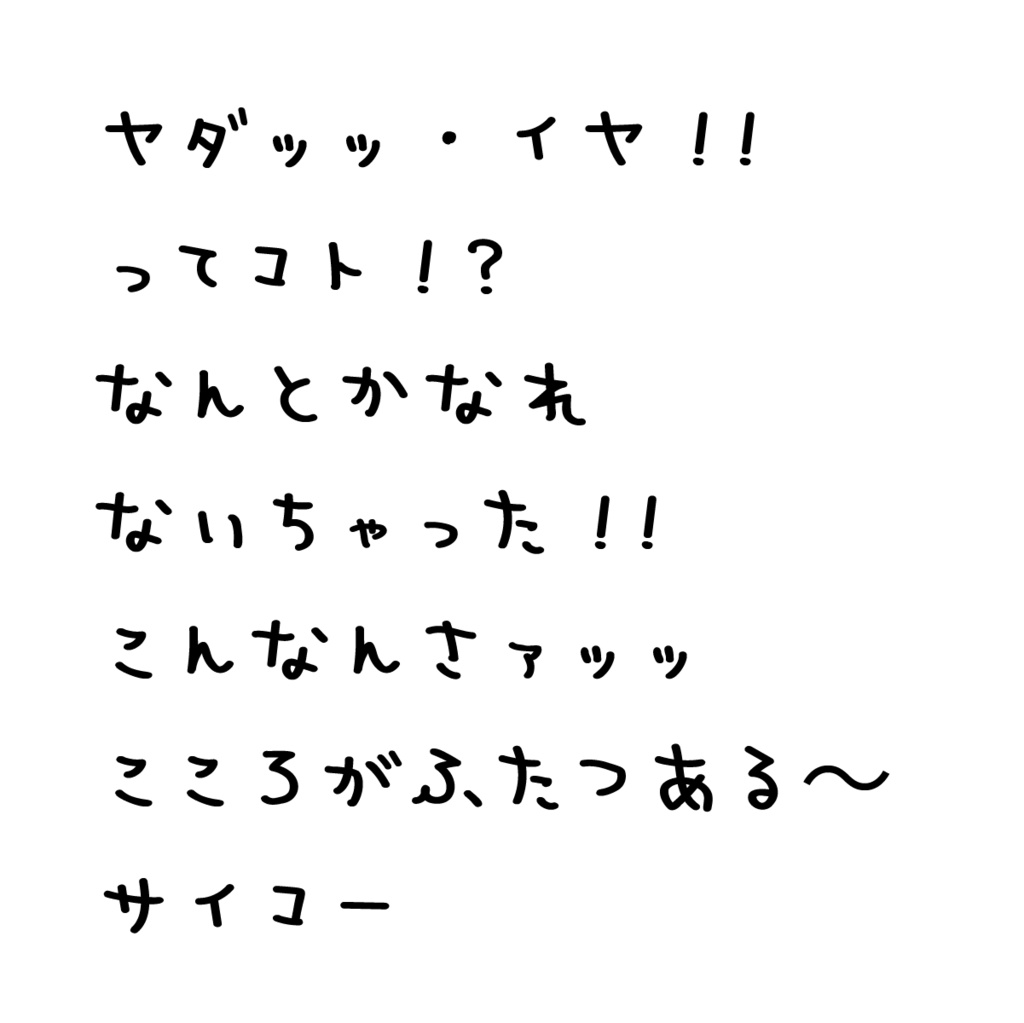
ちいかフォント(フリーフォント)
【25.04.02更新】 ・一部の文字を修正対応いたしました。 --- ちいかフォントは、「文字が、ちいかわのナガノ先生の字に似ているね。」と知人に言われたことをキッカケに制作した手書きフォントです。 自前の手書き文字を、少しだけナガノ先生の筆致に寄せて書いてみました。 キャラクターの吹き出しなどでぜひ活用ください! 無料版と投げ銭版(¥100)のフォント内容は同一です。 【収録文字】 ・全角ひらがな、カタカナ ・数字 ・大文字アルファベット(小文字も大文字として表示されます) ・一部の記号類 【利用規約】 ・商用・非商用を問わず利用可能です。 ・著作権を放棄していません。 ・当フォントを利用して発生した、いかなる損害についても作者は責任を負いません。 ・フォントデータをダウンロードした時点で利用規約に同意したものとみなします。 【禁止事項】 ・フォントデータの改変・無断転載・再配布・販売 ・当フォントを利用した制作物、ロゴなどの商標登録